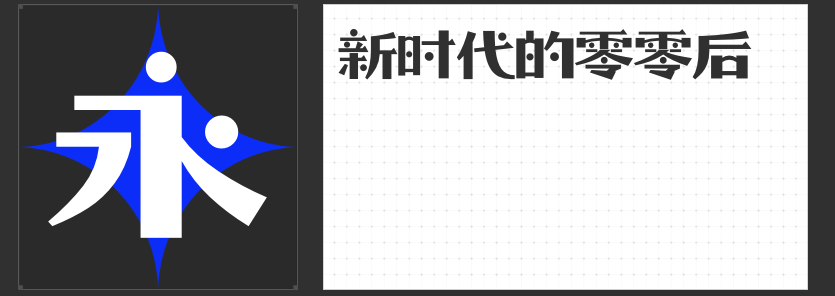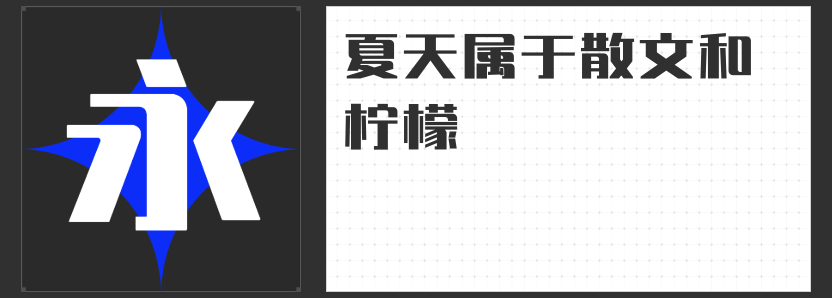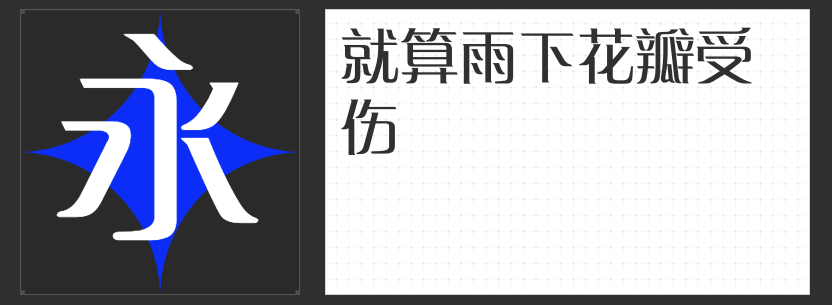
用字体点亮设计中的魅力!印刷艺术中的创意字体推荐
在印刷艺术的世界里,字体的选择如同一把钥匙,能开启视觉与情感的大门。今天,我们为您精选了四款专为印刷设计而生的创意字体,它们各具特色,旨在为您的作品增添无限魅力与视觉冲击力。
这款字体以其独特的斜度与利索的转折,展现出一种力量与美感的完美结合。它摒弃了过度的装饰,专注于细节的优化,使得字体在视觉上更加流畅,降低了阅读障碍,为读者提供了更加舒适的阅读体验。在印刷设计中,励字钧线黑简 微黑的全直线设计不仅符合当代审美趋势,更让字体本身成为画面的亮点,独树一帜,别具一格。
二、励字励倩简
这款字体以扁平硬笔的书写轨迹为基础,笔锋被巧妙地设计成微小的圆弧,使得字体整体看起来柔润舒畅,字型方正饱满。笔划粗细对比适中,既保持了字体的清晰度,又增添了一份婉转妩媚的气质。励字励倩简看似平淡无奇,却能在细微之处触动人心,给人以美的享受。在印刷作品中,它能够完美融入各种设计风格,为作品增添一份独特的韵味。
三、励字光芒简 超黑
这款字体以黑体为原型,经过精心打造,笔画粗壮,线条分明,视觉冲击直观有力。它适用于广告设计、平面设计、产品包装、报刊杂志等多个领域,能够迅速吸引观众的注意力。励字光芒简 超黑不仅保留了黑体的简洁明了,更在视觉上进行了强化,使得字体在印刷作品中更加突出,成为传递信息的有力工具。
四、字恋狂零零后简繁
这款字体充满了青春与活力,字体中融入了圆形小球元素,无规则地散落在每个字当中,显得调皮可爱。部分笔画被设计成拱形的弧线,曲直结合,相映成趣。字恋狂零零后简繁不仅适合用于年轻化的印刷设计作品,如时尚杂志、海报等,更能为作品增添一份独特的创意与趣味性。
这四款创意字体各具特色,适用于不同类型的印刷设计作品。选择适合您需求的字体,让文字在印刷艺术中绽放出无限魅力吧!